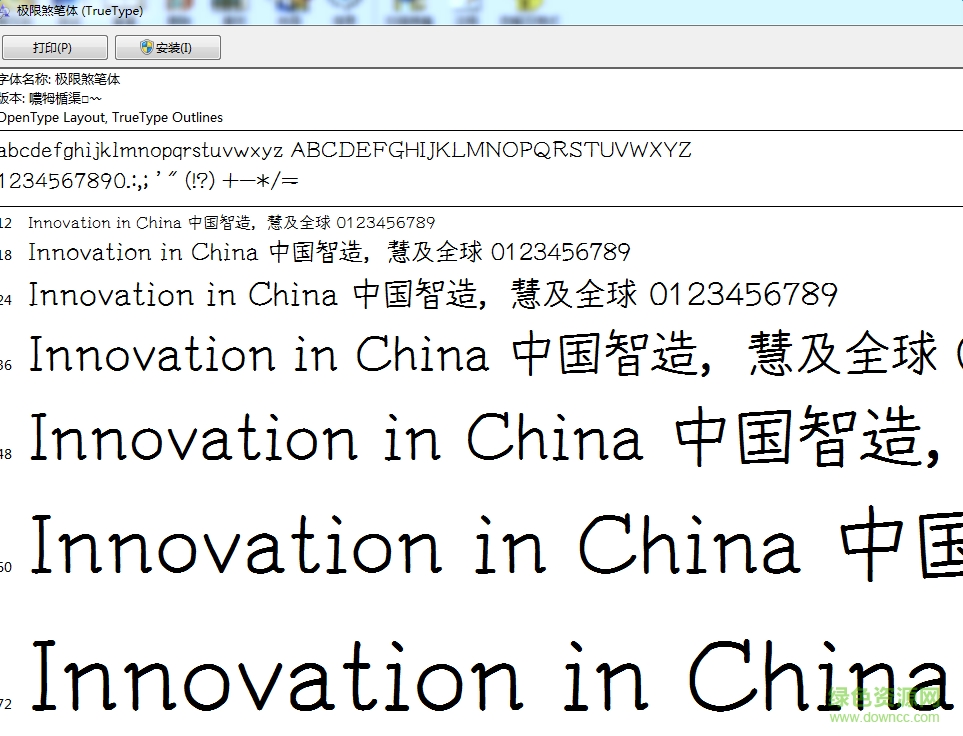
極限煞筆字體是一款古典線條風(fēng)格字體軟件,極限煞筆體筆畫耿直灑脫、彎曲看似無章法,卻別有一番韻味,整體效果不錯,還有更多好看字體歡迎來綠色資源網(wǎng)下載體驗!
極限煞筆字體是一款應(yīng)用于藝術(shù)設(shè)計方面的簡體中文字體,該字體筆畫細(xì)膩,尾部的甩尾有力且有豐富的筆觸細(xì)節(jié),大字效果突出且引人注目;并且最大程度還原作者書寫字形,細(xì)節(jié)表現(xiàn)完整,且字庫完整,可以廣泛應(yīng)用于名片設(shè)計、新聞媒體、宣傳海報、ppt、影視制作以及內(nèi)容用字等領(lǐng)域。